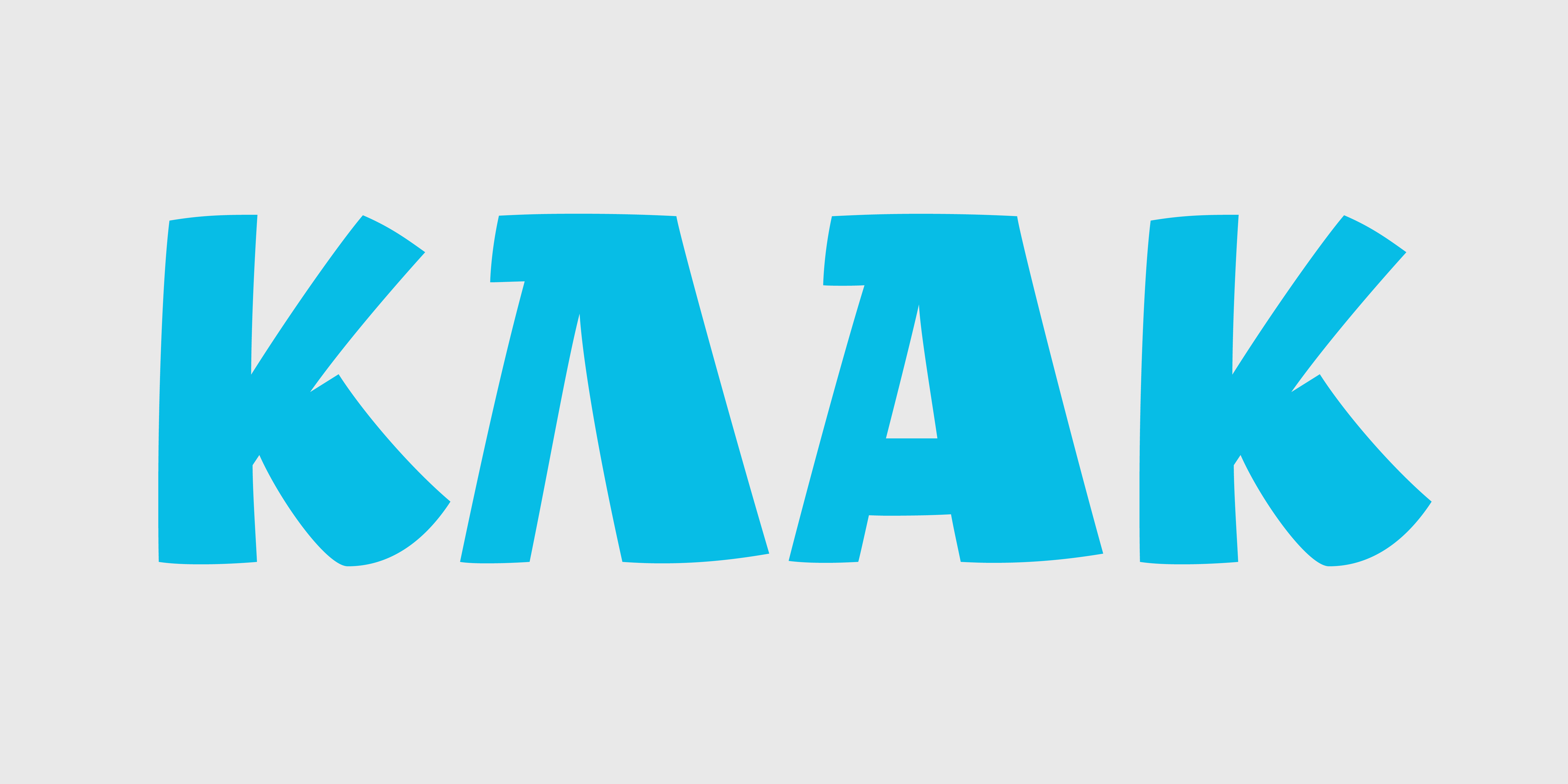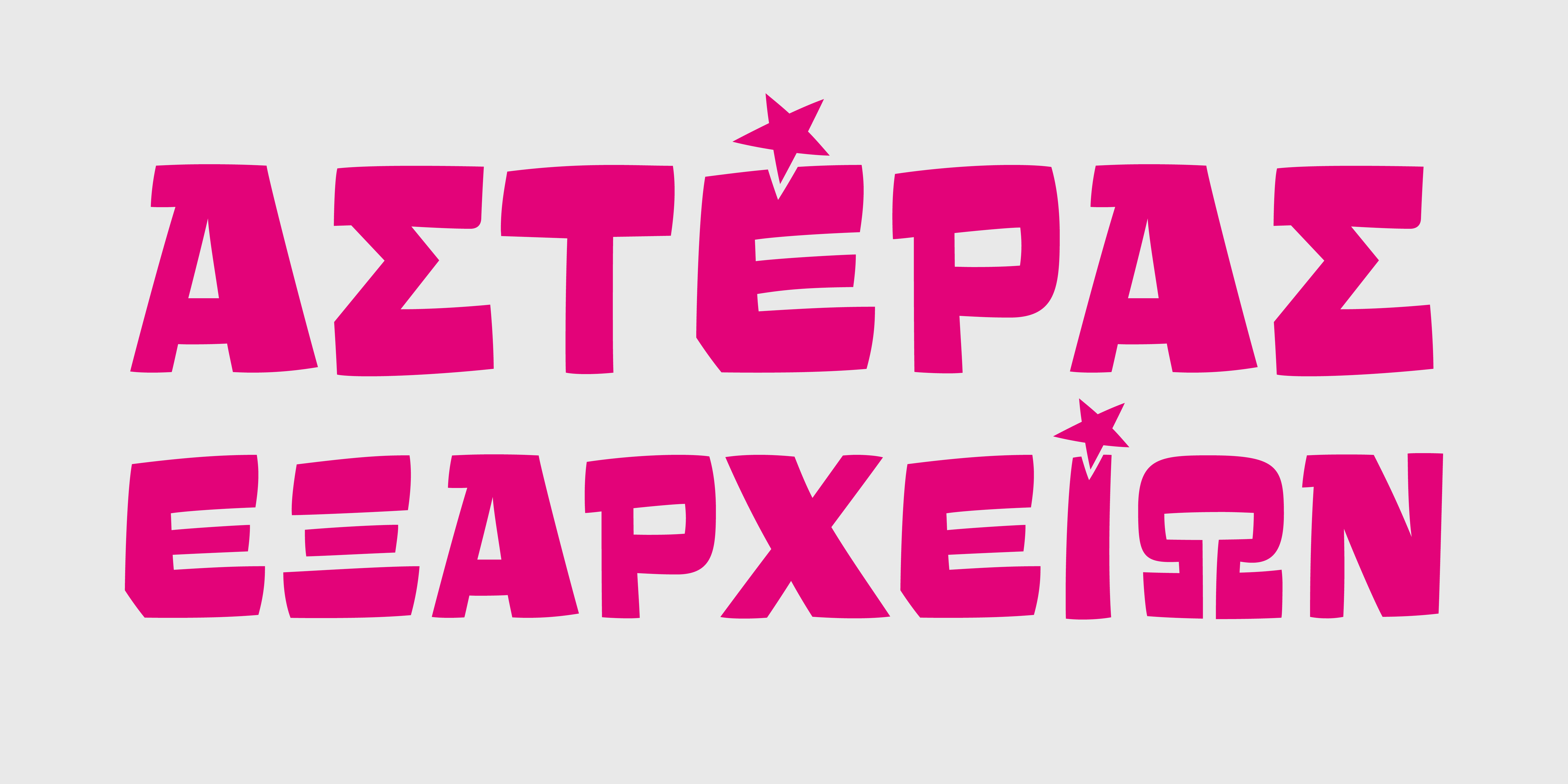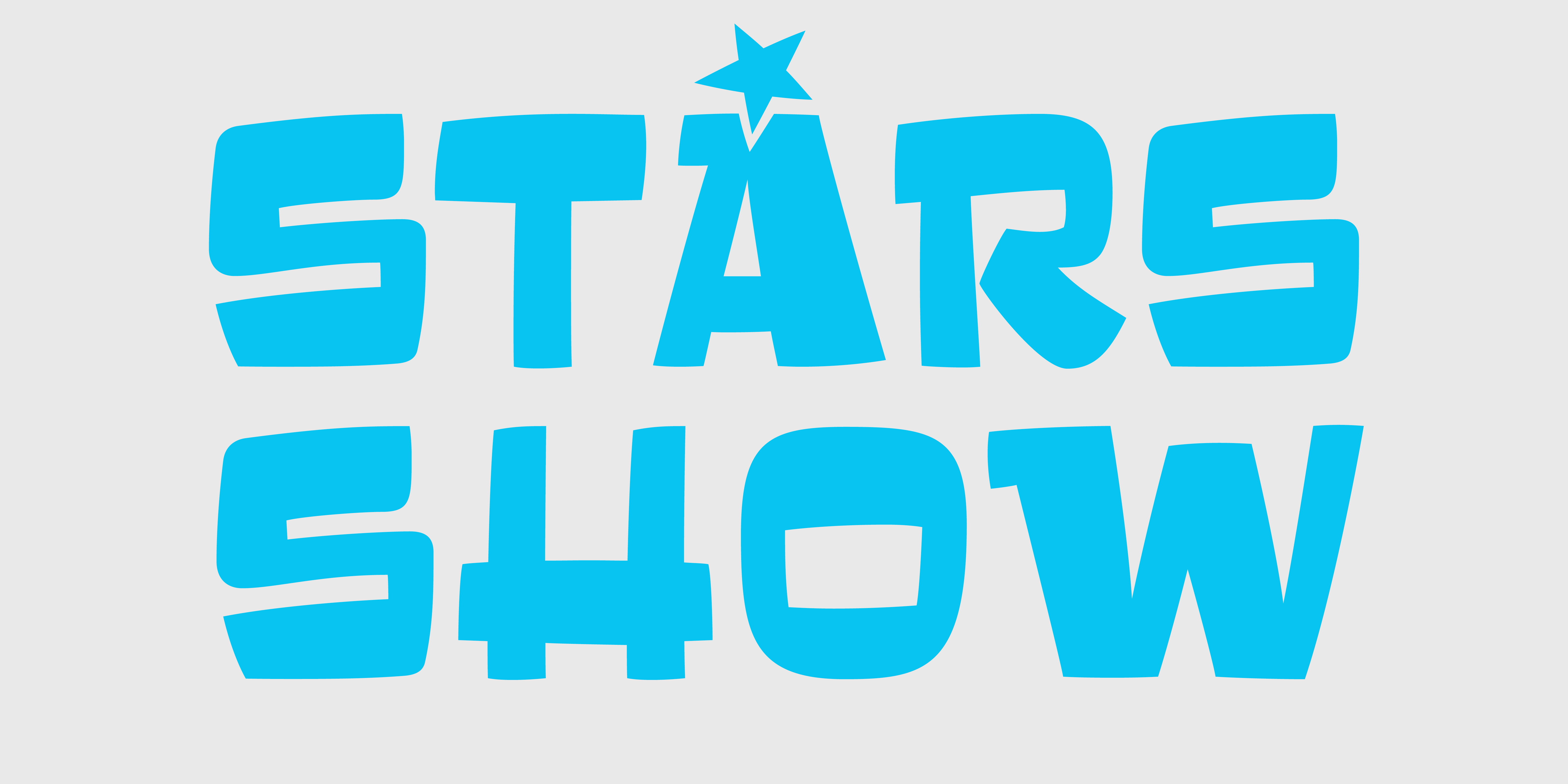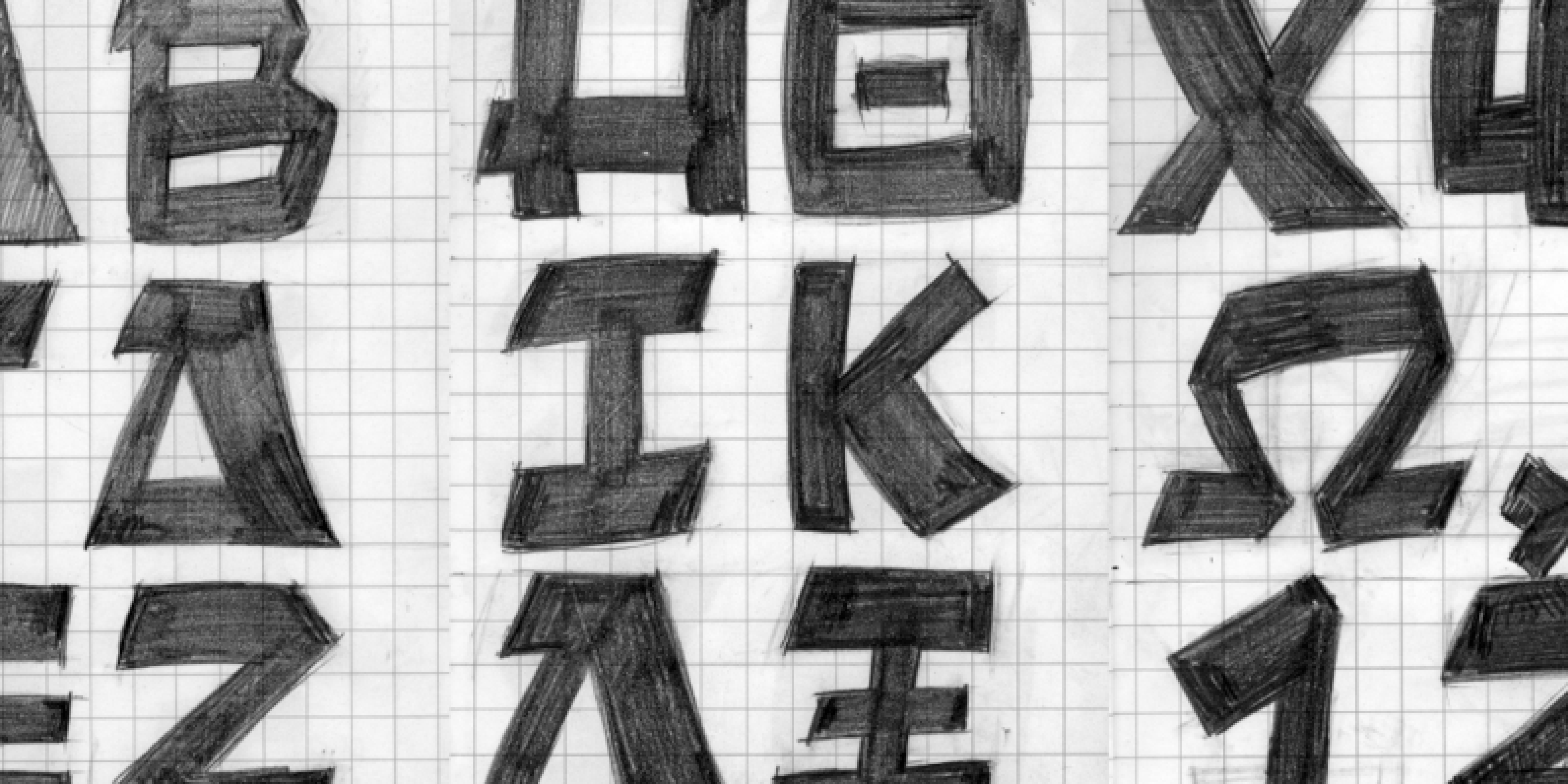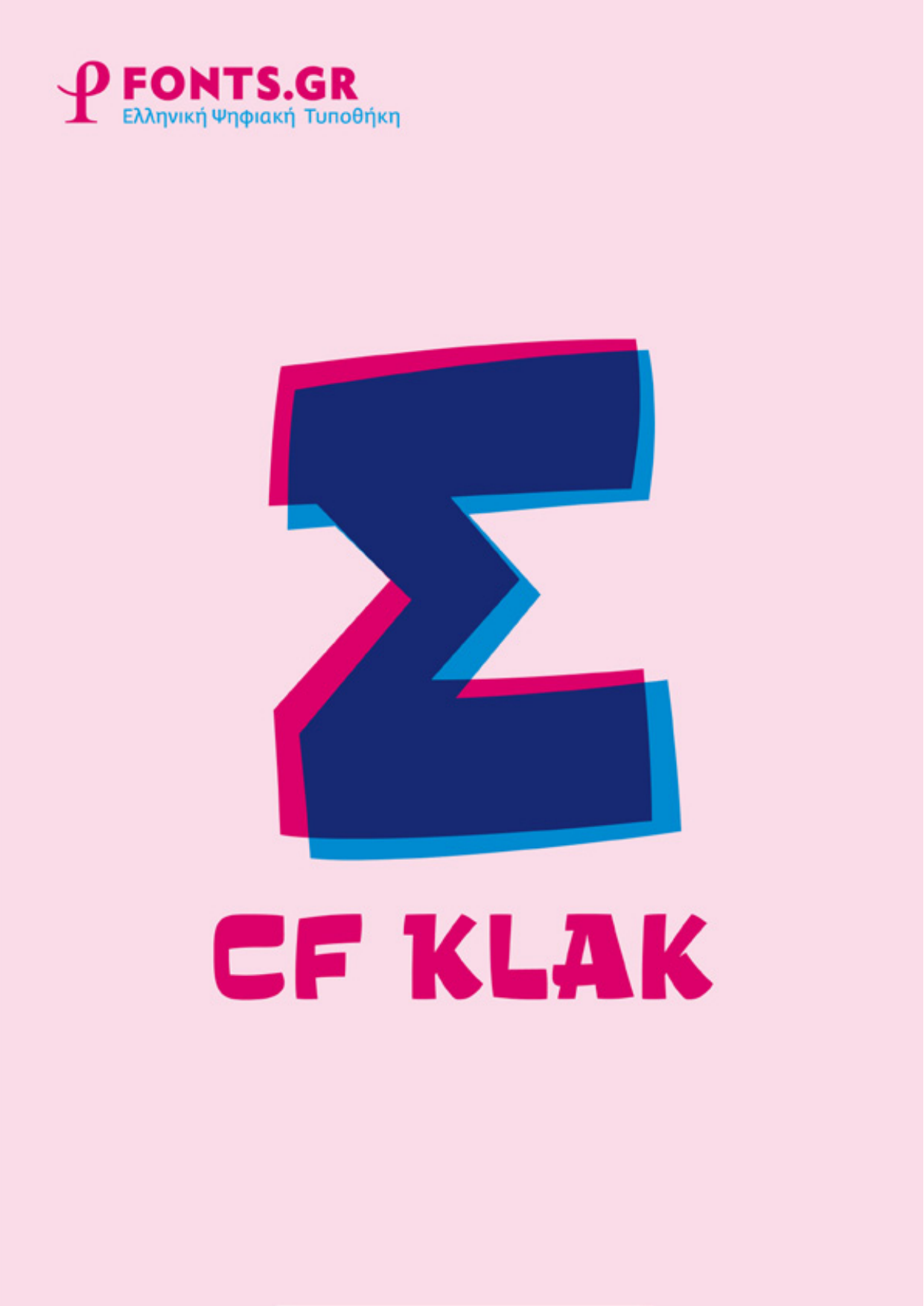
Klak
Η CF KLAK, είναι μια κεφαλαιογράμματη σειρά τίτλων, εμπνευσμένη από τα χειρόγραφα στοιχεία των διαφημίσεων και τίτλων του ελληνικού κινηματογράφου των δεκαετιών '50, '60 και '70. Τα στοιχεία είναι παχιά, τετραγωνισμένα, με αντεστραμμένη θέση λεπτών-χοντρών πινελιών. Η CF KLAK περιλαμβάνει ένα πλήρες σύνολο εναλλακτικών χαρακτήρων, με περισσότερο στογγυλεμένες γωνίες και κάποιες έντονες καλλιγραφικές λεπτομέρειες, ώστε να μπορεί ο σχεδιαστής να προσεγγίσει την τυχαιότητα του χειρόγραφου στιλ – καθώς και ελληνικά φωνήεντα τονούμενα με αστέρι αντί για τόνο.